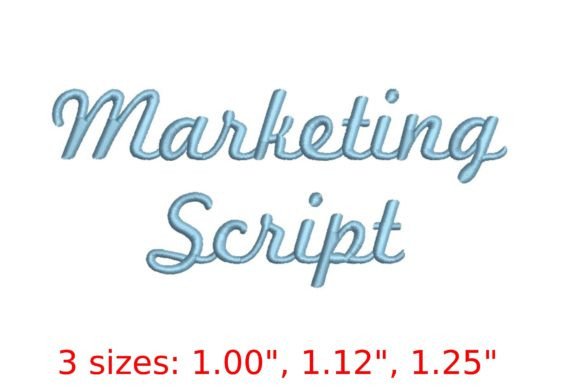
Marketing Script Embroidery Font
Doğru tasarım öğelerini bulmak zor olabilir, ancak Marketing Script Embroidery Font, çalışmanızı anında bir üst seviyeye taşıyan olağanüstü bir koleksiyon sunar.
İster İsteğe Bağlı Baskı (POD) ürünleri, ister düğün davetiyeleri veya sosyal medya grafikleri oluşturuyor olun, Marketing Script Embroidery Font ideal bir uyumdur.